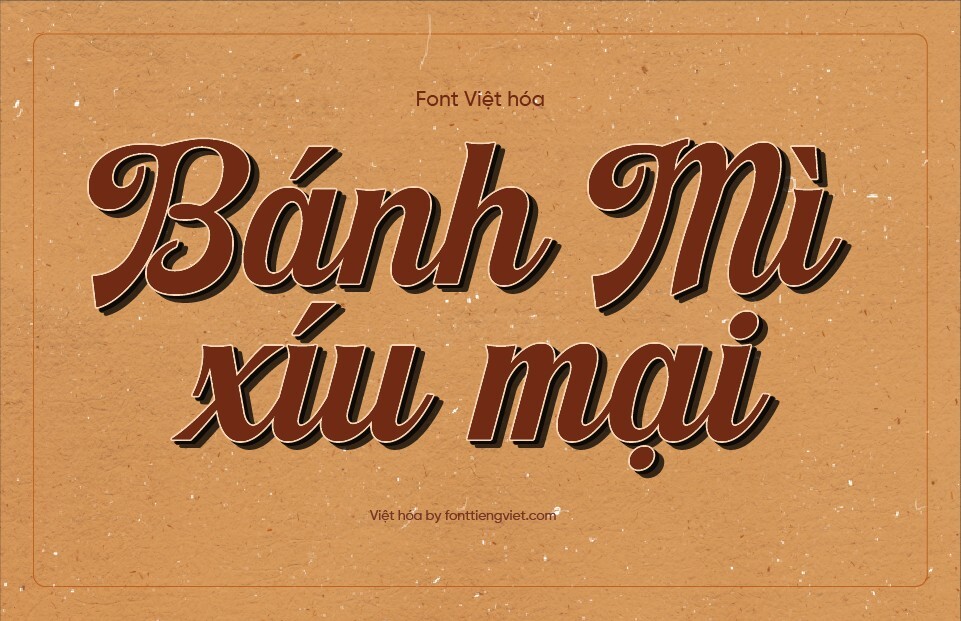
Font Việt hóa TF Vortigra Việt Hóa
Font Việt hóa TF Vortigra
Tên font: Font Việt hóa TF Vortigra
Font Việt hóa TF Vortigra là một sự sáng tạo độc đáo, nổi bật với những nét đậm và mạnh mẽ. Được thiết kế với phong cách hiện đại, Vortigra không chỉ thu hút ánh nhìn mà còn mang lại sức sống cho mọi ấn phẩm mà nó xuất hiện.
Với tính năng linh hoạt, Vortigra rất phù hợp cho các thiết kế in ấn, đặc biệt là tiêu đề các ấn phẩm quảng cáo. Đường nét sắc sảo và mạnh mẽ của font chữ này giúp nổi bật những thông điệp quan trọng, đồng thời tạo ấn tượng ngay lập tức với người xem.
Khi sử dụng Vortigra, bạn không chỉ mang đến sự mới mẻ cho thiết kế mà còn thể hiện phong cách cá nhân độc đáo. Hãy chọn font chữ Vortigra cho các dự án quảng cáo của bạn để tạo nên những ấn phẩm bắt mắt và ấn tượng!